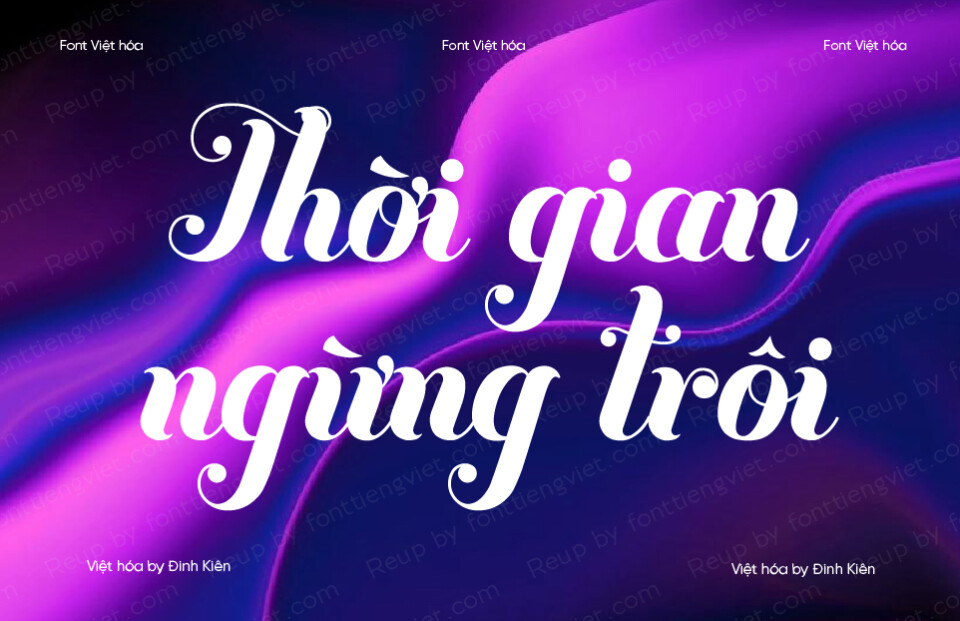
Font Việt hóa UTM Buttermilk – Nét Chữ Bay Bổng Cho Thiết Kế Sáng Tạo
Giới thiệu về Font Việt hóa UTM Buttermilk
Trong thế giới thiết kế đồ họa tại Việt Nam, nhu cầu tìm kiếm các bộ Font Chữ đẹp mắt và hỗ trợ gõ tiếng Việt luôn là ưu tiên hàng đầu. Một trong những cái tên nổi bật nhất chính là Font Việt hóa UTM Buttermilk. Đây là một phông chữ thuộc dòng Script với những đường nét uyển chuyển, mềm mại nhưng vẫn giữ được sự hiện đại và tinh tế. Bộ font này đặc biệt phù hợp cho các bạn học sinh, sinh viên hoặc giáo viên muốn trang trí bài thuyết trình, làm thiệp chúc mừng hoặc thiết kế các ấn phẩm truyền thông học đường sinh động hơn.
Đặc điểm nổi bật của font chữ
Font Việt hóa UTM Buttermilk sở hữu cấu trúc chữ viết tay độc đáo với các nét thanh nét đậm rõ rệt. Khoảng cách giữa các ký tự được căn chỉnh tỉ mỉ, giúp văn bản trở nên thanh thoát và dễ nhìn. Nhờ được việt hóa bởi đội ngũ UTM, người dùng có thể hoàn toàn yên tâm sử dụng bảng mã Unicode để gõ các dấu tiếng Việt mà không lo bị lỗi hiển thị. Đây là lựa chọn lý tưởng cho những dự án yêu cầu tính thẩm mỹ cao và sự cá nhân hóa đậm nét.
Cách ứng dụng Font Việt hóa UTM Buttermilk hiệu quả
Sử dụng trong giáo dục và thiết kế
Với vẻ ngoài ngọt ngào như chính tên gọi của mình, Font Việt hóa UTM Buttermilk thường được dùng để thiết kế bìa sách, tiêu đề báo tường hoặc các bảng vinh danh học sinh. Để đạt hiệu quả thị giác tốt nhất, bạn nên kết hợp nó với các phông chữ không chân (Sans-serif) đơn giản nhằm tạo sự cân bằng. Đừng quên điều chỉnh kích thước chữ vừa đủ để người xem dễ dàng tiếp nhận thông tin.
Kết luận về bộ font chữ đẹp